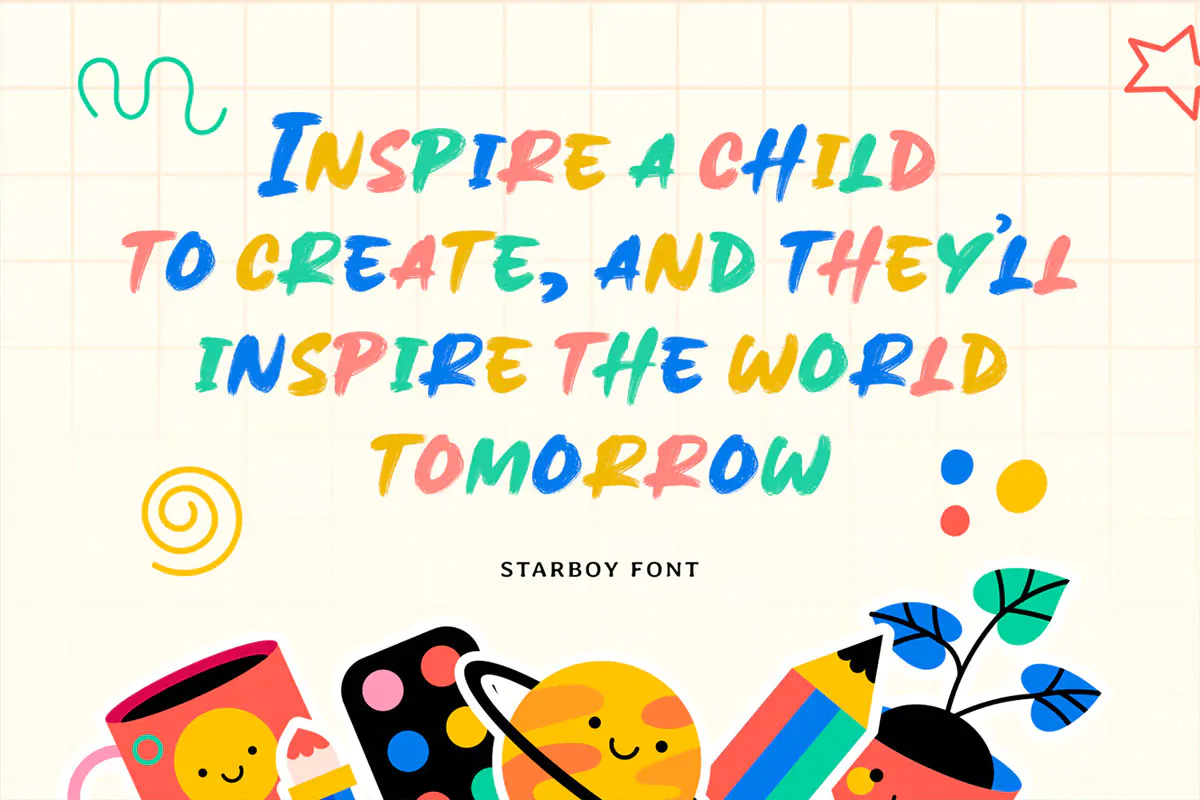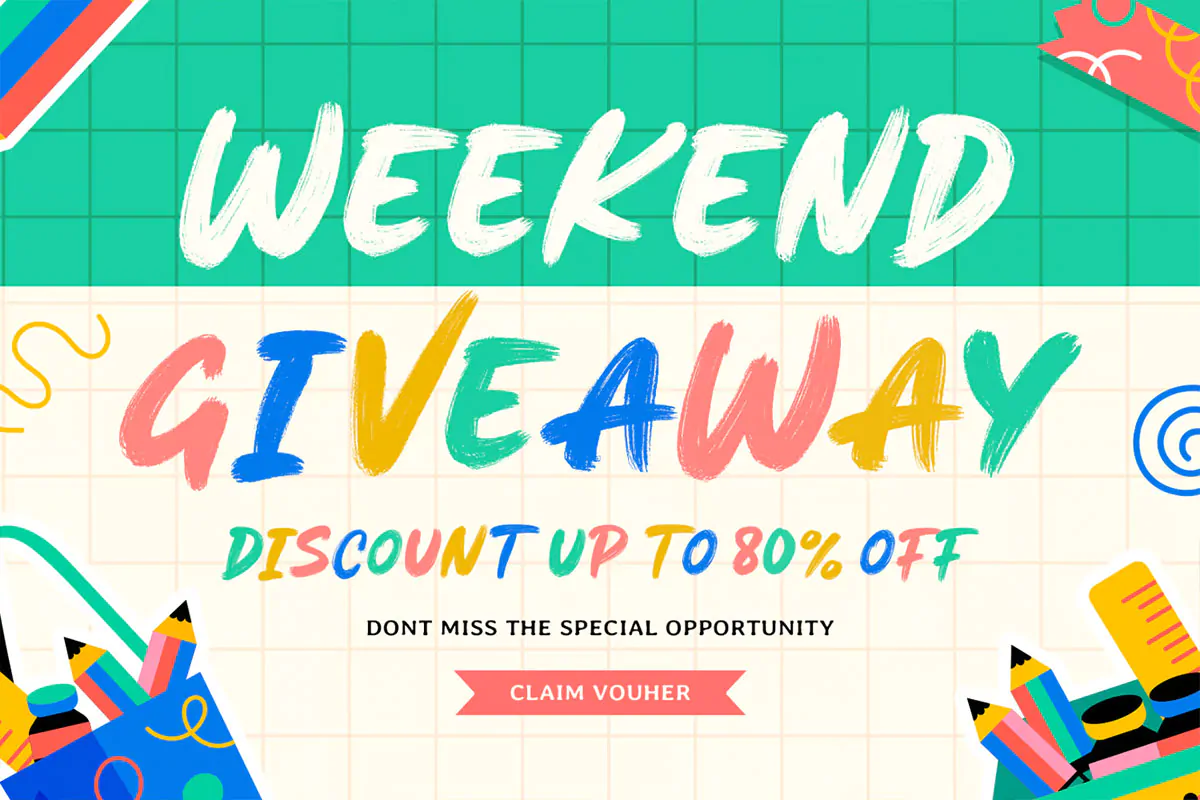
فونت قلمویی کودکانه Starboy
فونت قلمویی کودکانه
فونت قلمویی کودکانه Starboy یک قلم انگلیسی فوق العاده زیبا و جذاب است که میتوانید در طرح و پروژههای مختلف از آن استفاده کنید.
برای تایپوگرافی، پوستر، هویت بصری و محتوای چاپی یا دیجیتال قابل استفاده است.